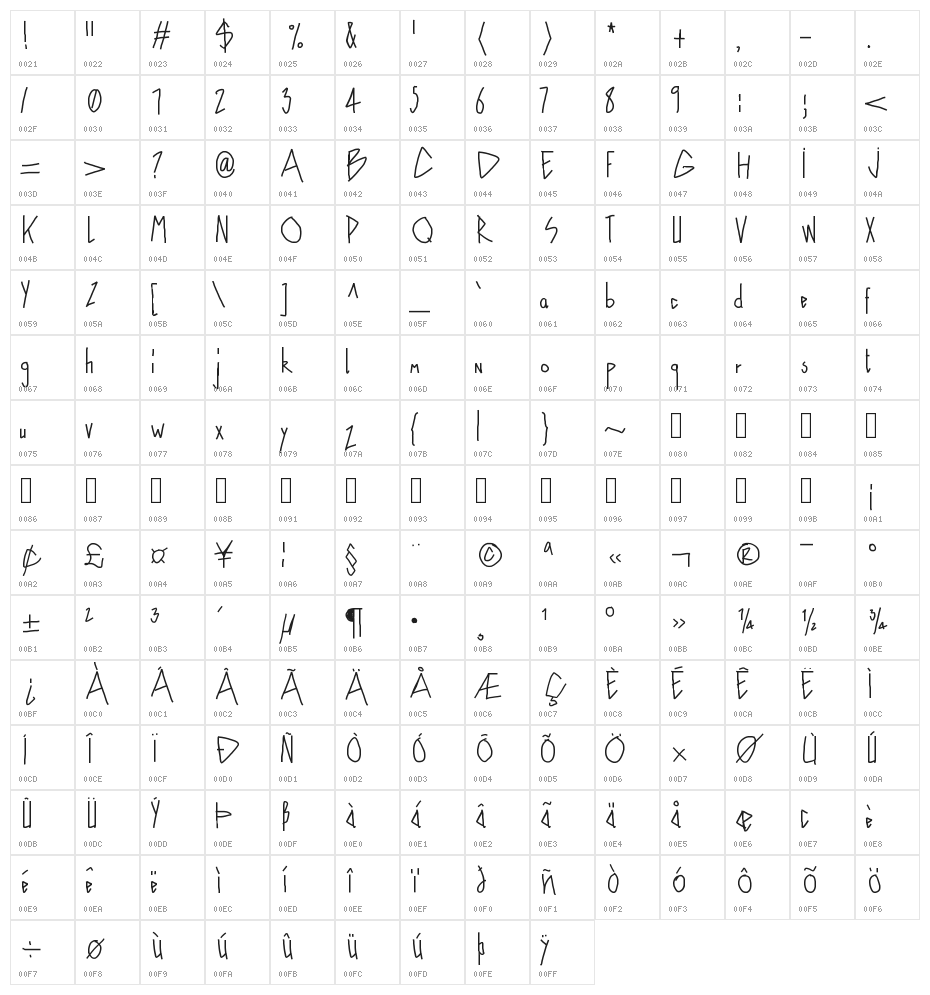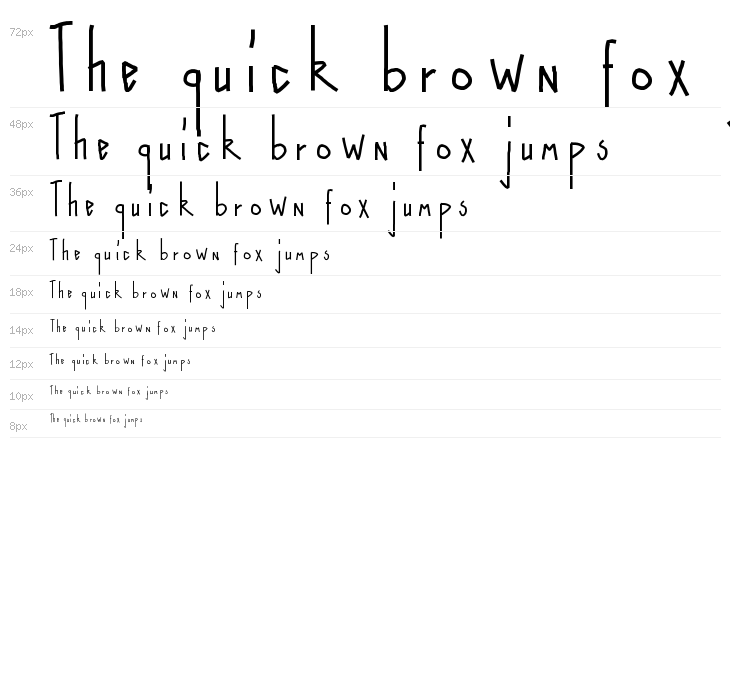
Naive Font
| Caso d'uso | Headlines, Logos, Informal Text |
| Progetti proposti | Ideal for children's books, creative posters, casual invitations, and playful branding. |